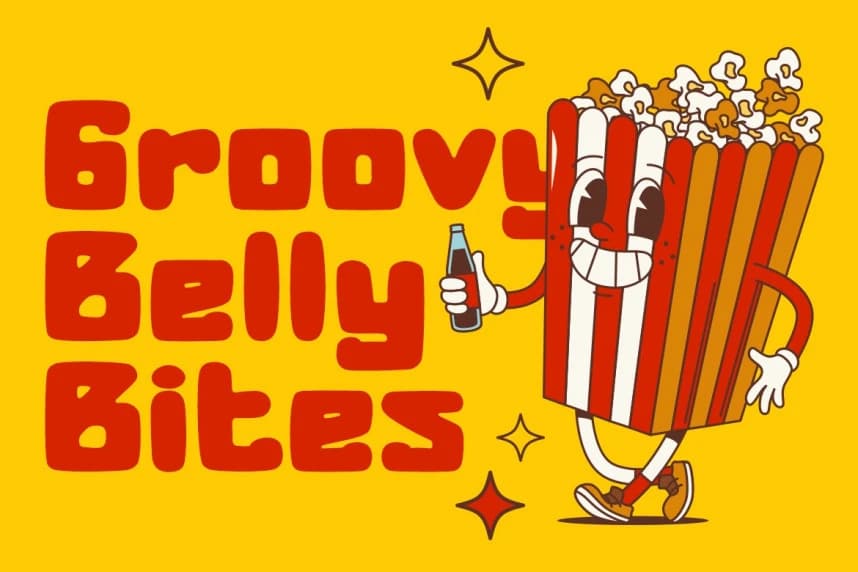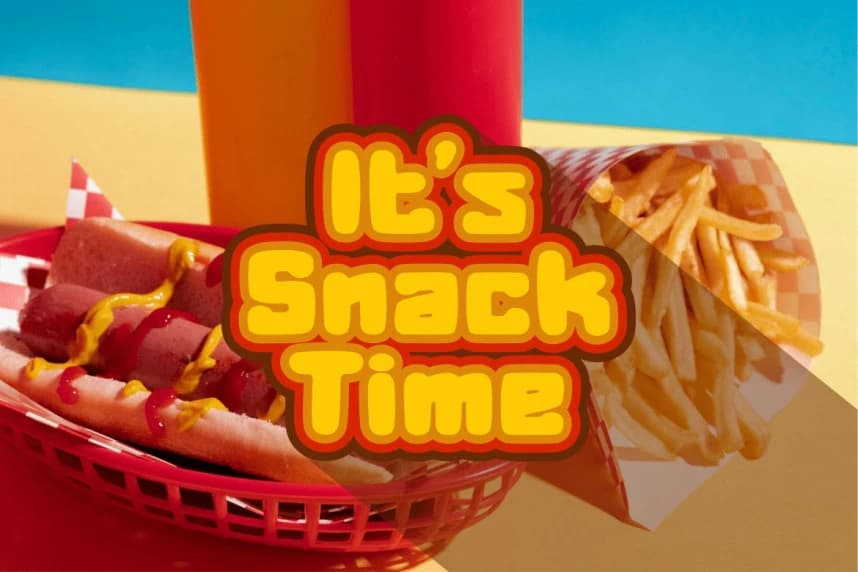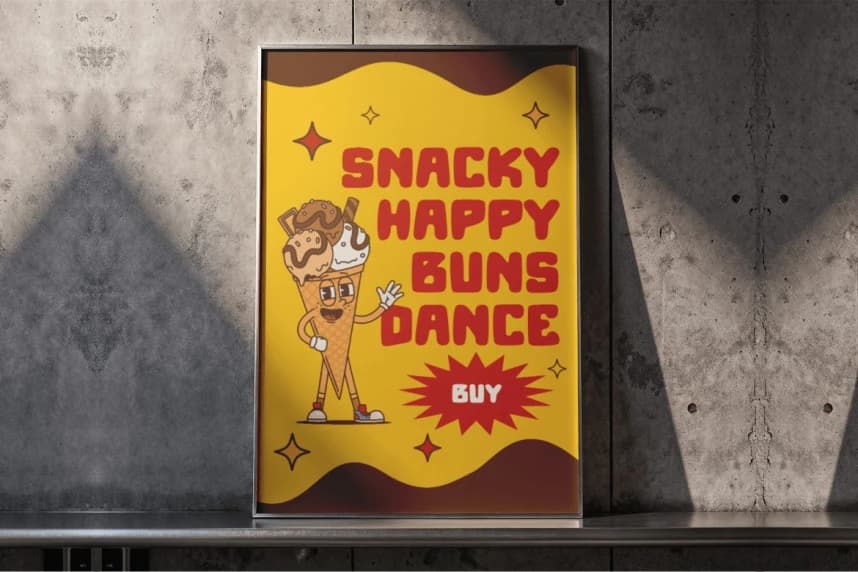
Chubzy Funk Display Font
Chubzy Funk Display Font – Fun Fat Font, sokak yemeği kültürünün enerjisinden, groovy titreşimlerden ve retro pop estetiğinden ilham alan cesur, yuvarlak hatlı ve son derece oyunbaz bir yazı tipidir. Bu tipografideki her karakter, kalın ve hacimli bir şekilde tasarlanmıştır.
Chubzy Funk Display Font – Fun Fat Font, sokak yemek kültürünün enerjisinden, groovy hissi ve retro pop estetiğinden ilham alan cesur, yuvarlak ve neşeli bir yazı tipidir. Bu yazı tipindeki her karakter, kalın bir tasarımla işlenmiştir.